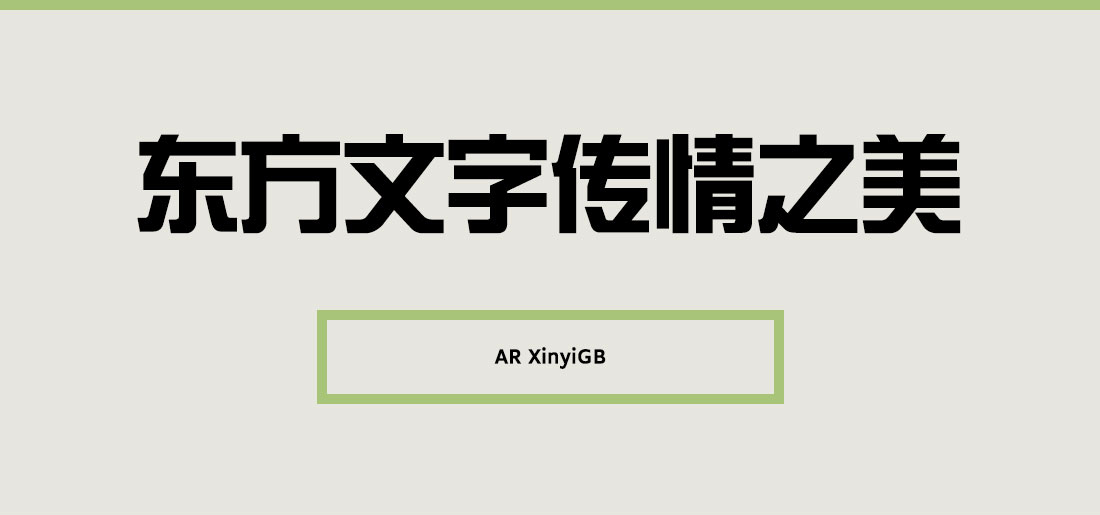
- XinyiGB는 선의 방향이나 구조를 기존의 고딕과는 조금 다르게 가져간 폰트이다.
각지고 부드러운 느낌을 주어 상업용 광고, 신호 및 인쇄물의 헤드 라인에 적합하도록 디자인 되었다.
폰트명 뒤에 붙은 GB라는 표기는 간체의 문자코드를 뜻한다. 간체란 중국에서 주로 사용하며 필획을 줄이고 자형을 간단하게 만든 한자다. 대만, 홍콩, 마카오 등에서 사용하는 번체(B5)와는 달라 잘못 적용할 경우 글립이 제대로 표기되지 않거나 다른 글립으로 표기되는 문제가 발생할 수 있다.